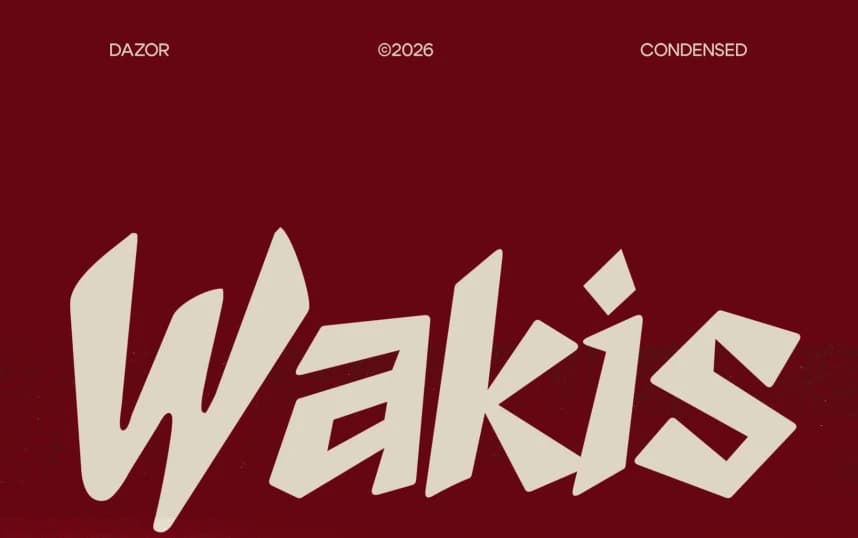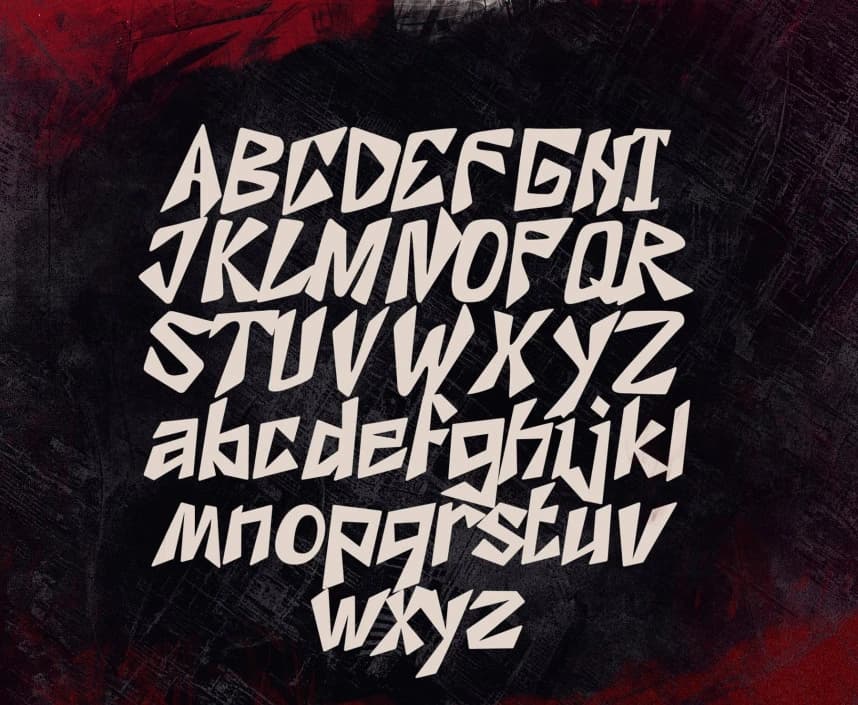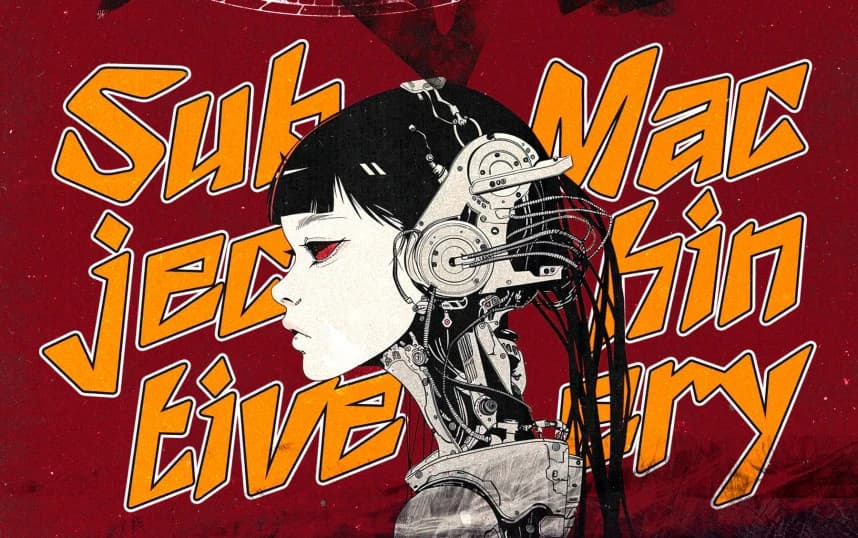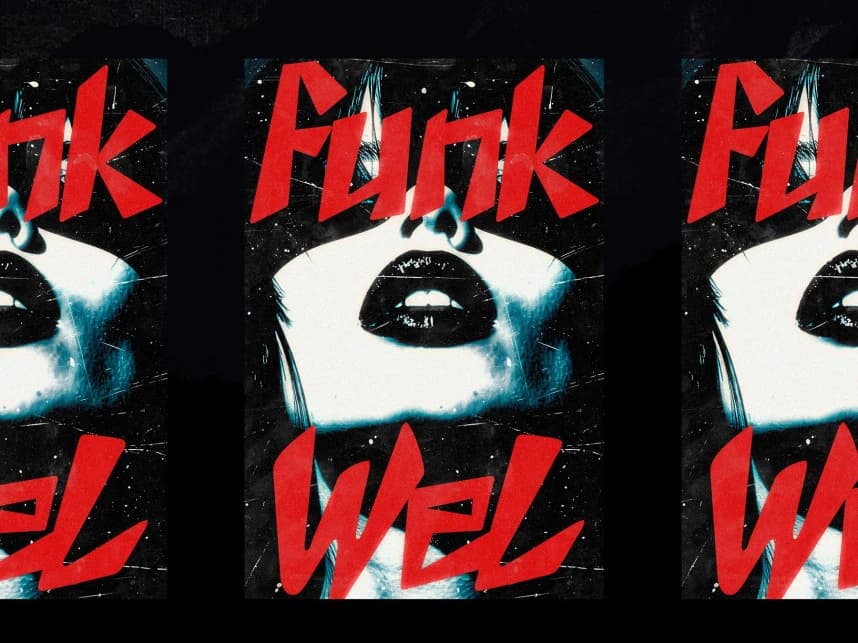
Wakis Display Font
Wakis Display Font - Ham, el yapımı bir his veren kaotik bir display yazı tipidir. Keskin, düzensiz biçimler ona grafiti havası kazandırır ve bu hava hafif bir futuristik, siberpunk dokunuşla karışır. Gür, dağınık ve enerjisi yüksek bir görünüme sahip; posterler, kapaklar ve cesur bir tavır isteyen
Wakis Display Font - Ham bir dokunuşa sahip kaotik bir gösterim yazı tipi. Keskin, düzensiz şekiller ona grafiti hissi verir; bu da hafif fütüristik, siberpunk etkisiyle karışır. Gürültülü, dağınık ve enerjisi yüksek görünüyor; posterler, kapaklar ve cesur bir tavır gerektiren her şey için mükemmeldir.
Wakis Display